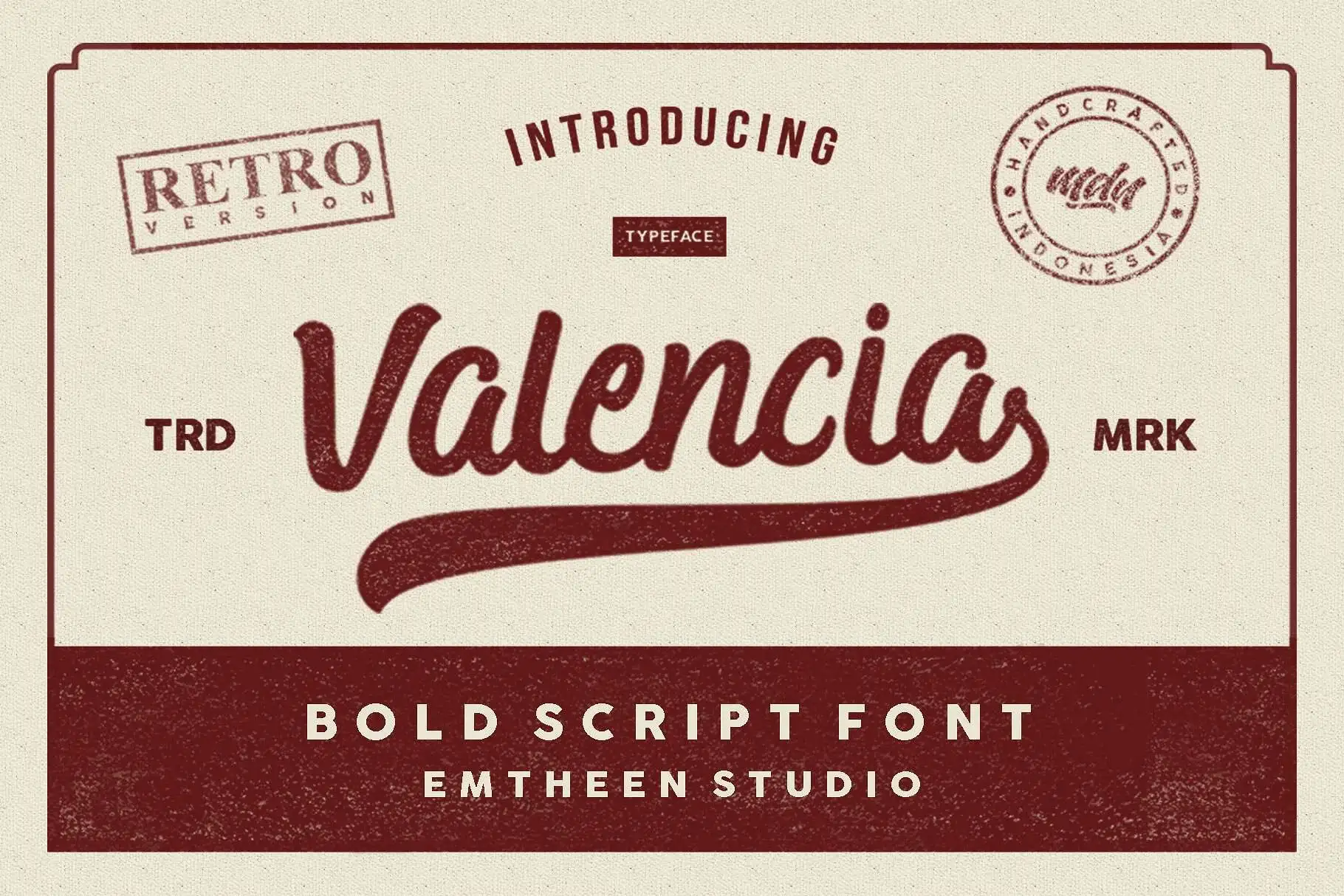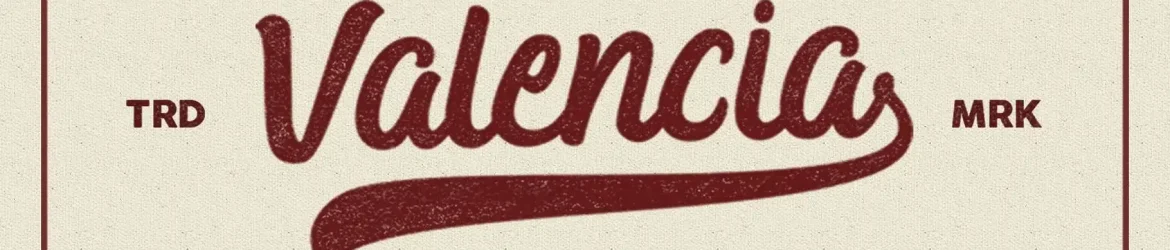
Valencia Script Font – Download Grátis
Introduzimos Valencia. Esta é uma fonte script bold criada por Emtheen, disponível nas categorias premium de CreativeMarket. Apesar do seu preço anteriormente ser elevado, está agora gratuita para download nesta data especial. Valencia é perfeitamente adaptável aos temas vintage e retro, mas também se destaca em estilos modernos. A adição de swashes torna-o ainda mais interessante, fazendo-o um recurso versátil para vários usos, como logotipos, cartazes, tipografia, capas de livros, roupas de marca, embalagens de produto e muito mais. Com sua elegância única, Valencia é uma excelente adição à sua coleção de fontes gráficas.